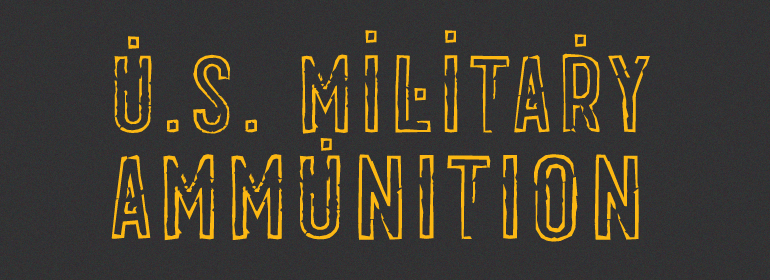
ITC Don't Panic™
ITC Don't Panic™,这款字体结构工整、笔画清晰,兼顾美观与易读性,适用于标题、正文、海报、包装、LOGO 等多种场景。字形优雅稳定,风格百搭耐看,适配日常排版与创意设计,让文字呈现更舒适、更具质感。ITC Don't Panic™一笔一画,皆是细节,以均衡的比例、流畅的线条打造舒适视觉体验,字形端正大气,风格简约现代。无论是商业设计、品牌宣传还是日常排版,都能轻松驾驭,让文字更有格调与力量。ITC Don't Panic™字体下载。
字体品牌: ITC(Monotype) 设计师:Thompson,Wayne 字体分类:衬线体 字体属性:外文 字符集:Unicode 发布时间: 2018
当你几乎无法控制局面的时候,ITC Don't Panic仿古的形状和粗犷的轮廓不会让你产生恐慌。当你真的失去控制,并且看不到任何希望的时候,ITC Panic的恐慌就会沿着情绪的轨迹进一步蔓延。汤普森说,这些字体的灵感来自于一天的邮件。我收到了一个信封,它看上去像是经历了一次艰难的旅程;上面印着的字体看上去很疲惫,参差不齐。“出乎意料的是,那张残破的信封唤醒了我。我很兴奋,想把这种外观复制为一种字体。”Thompson设计了ITC Don't Panic,然后站在后面看着它,觉得它需要一个焦虑不安的同伴。
ITC Don't Panic催生了一格积极的精神错乱的产物,ITC Panic。这两种设计都是全大写字母设计。事实证明,对汤普森来说,创造一个真正被扰乱的外观是一个挑战。 “我是想设计焦虑不安的字符,但他们看起来像是在演戏。
因此,我尝试了多次影印,但是那没有用。最终,我用激光打印了基本字符,再揉成一团,然后将它们展平并用厚底靴踩在上面。最终的结果被扫描并作为其它设计的基础。“Thompson在网站和多媒体方面的工作影响了他对字体和排印的兴趣,这种兴趣超越了计算机的酷炫、无感情的本质。”
ITC Don't Panic's distressed shapes and craggy outlines evoke the feeling you get when you're just barely in control of a situation. This is type design on the edge. ITC Panic is further down the emotional track, when you've actually lost control and there is no hope in sight. Thompson says the inspiration for these faces arrived one day in the mail. I received an envelope that looked like it had a rough trip; the type that was stamped on it had a tired, ragged appearance. Ironically, the haggard envelope woke me up. I got excited and wanted to replicate the look as a font of type." Thompson designed ITC Don't Panic, then stood back and looked at it and decided it cried out for a more agitated companion. ITC Don't Panic gave birth to the positively psychotic offspring, ITC Panic. Both are all-cap designs with alternate characters in the unshift position. Creating an authentically disturbed appearance proved to be a challenge for Thompson. "I tried to design agitated characters, but they looked staged. So I tried multiple photocopies, but that didn't work. Eventually, I laser-printed the basic characters, wadded up the lasers, then flattened them out and stomped on them with heavy boots. The end result was scanned and used as the basis for the rest of the design." Thompson's work on web sites and multimedia has influenced his interest in type and typography that transcends the cool, unemotional nature of the computer."